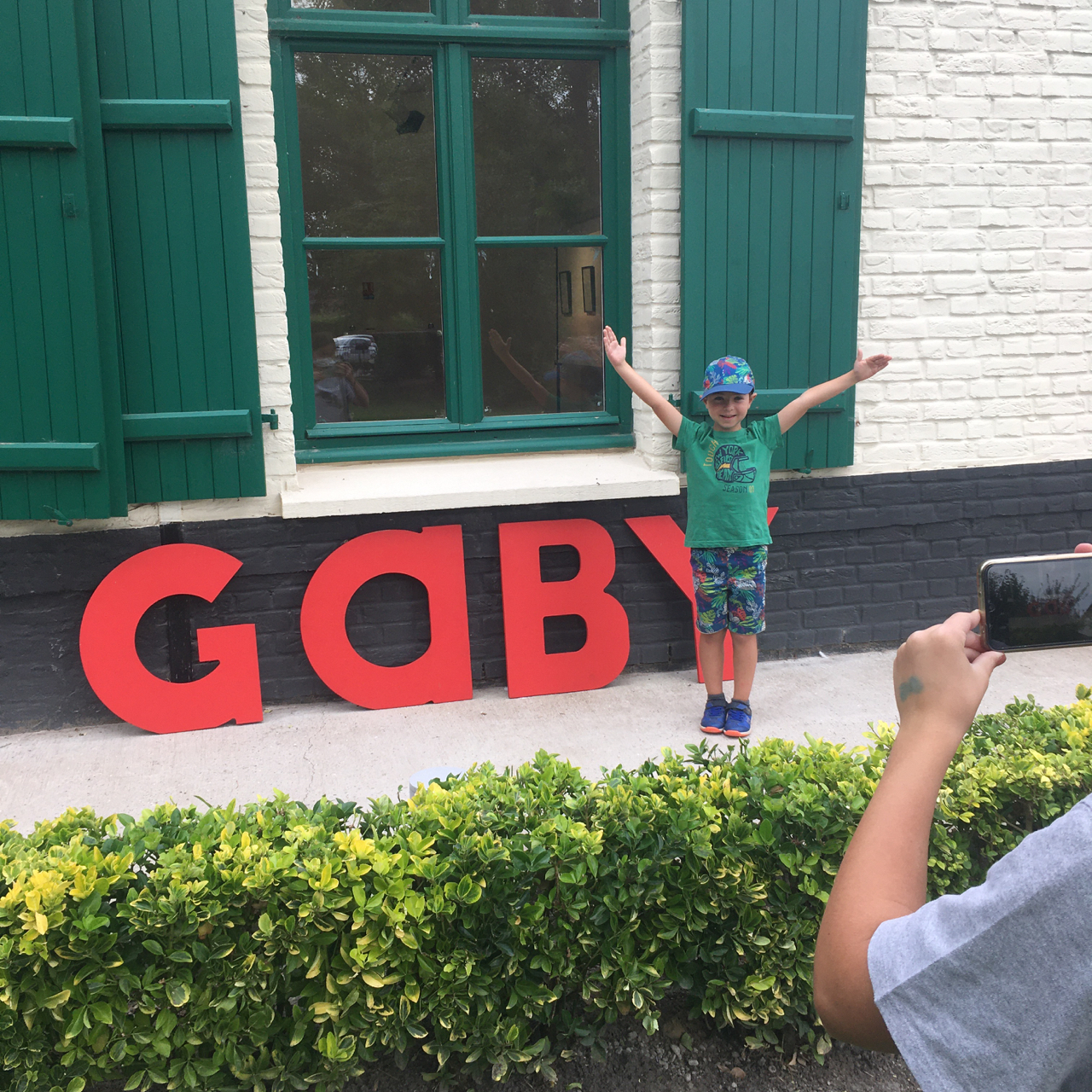
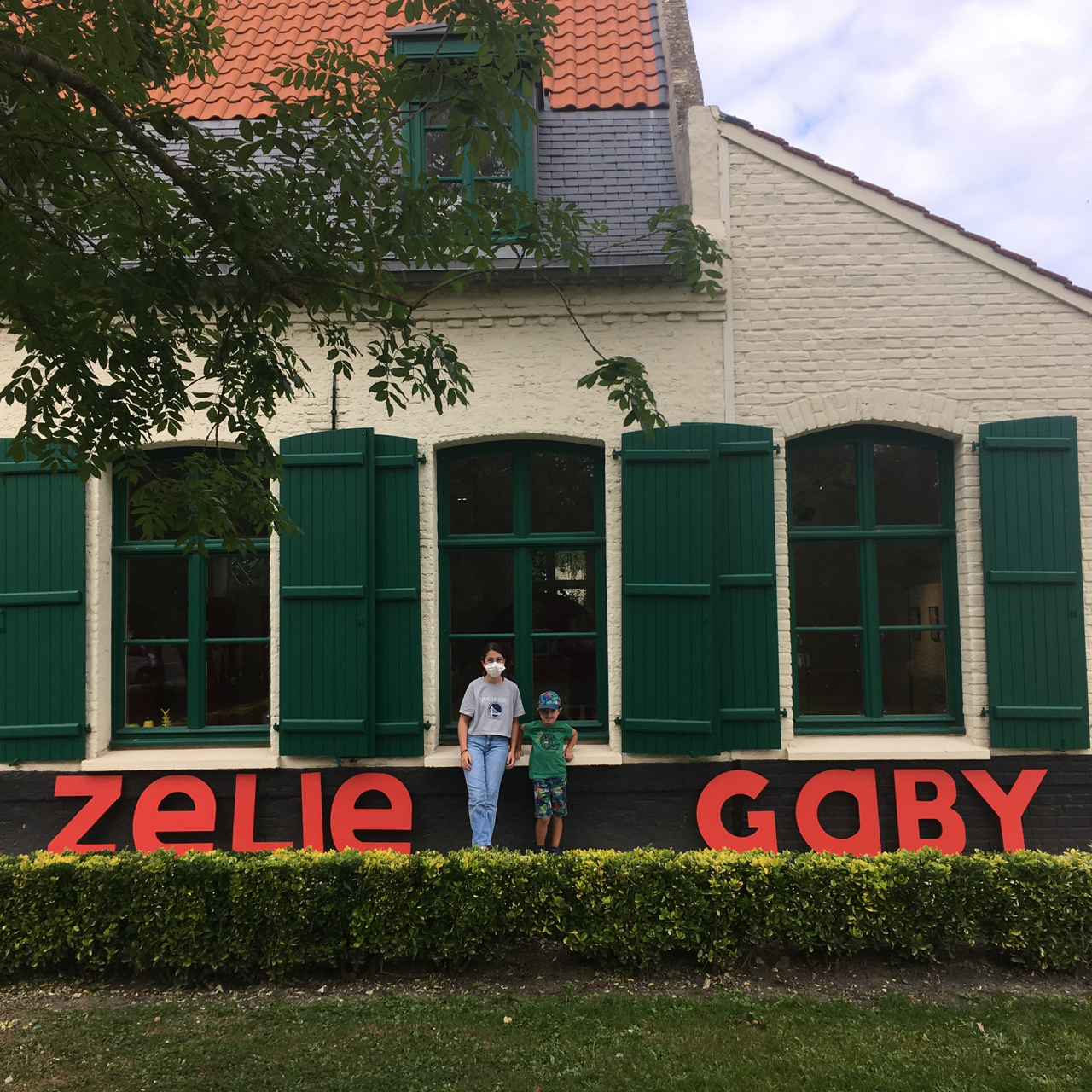
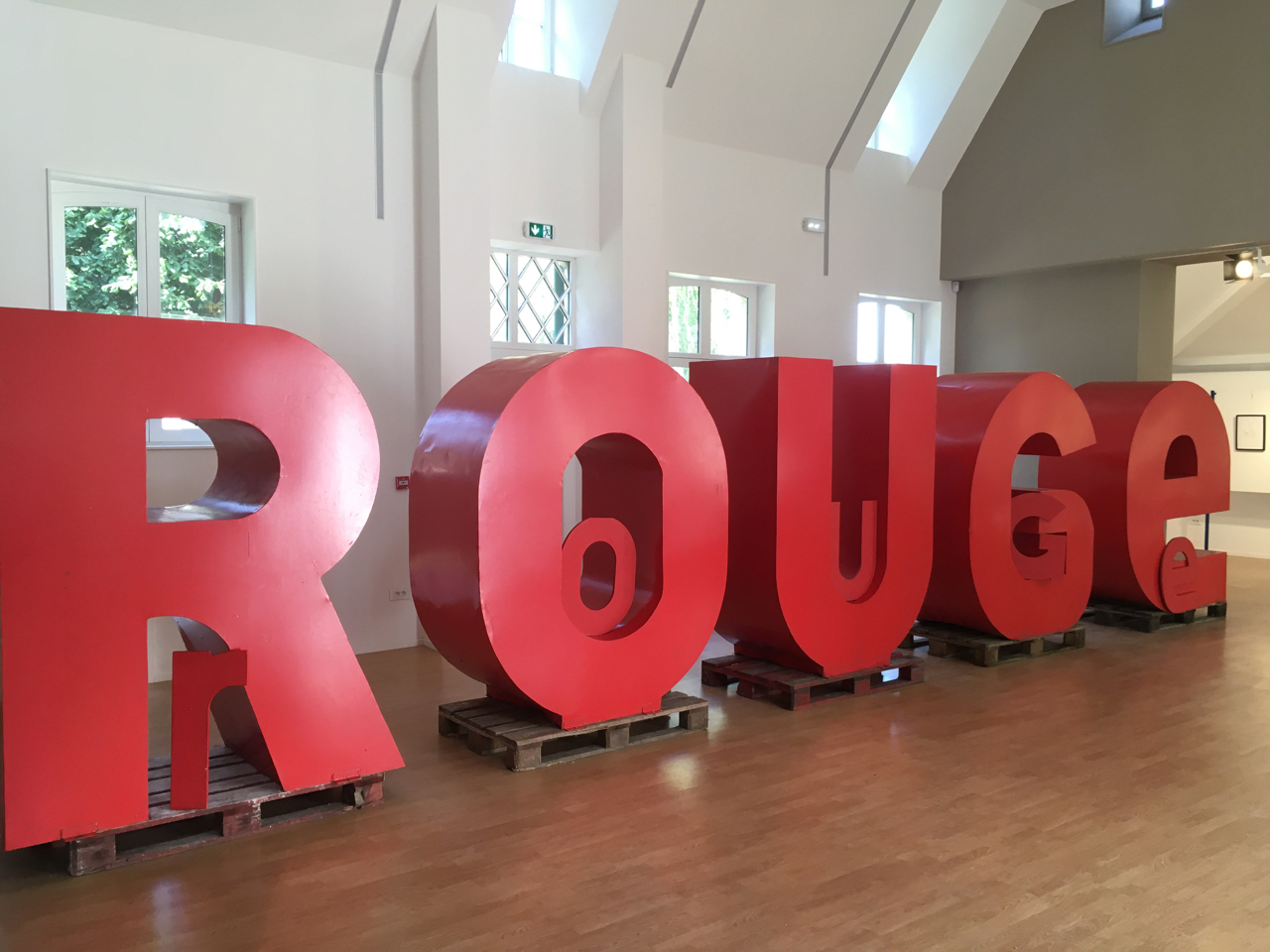
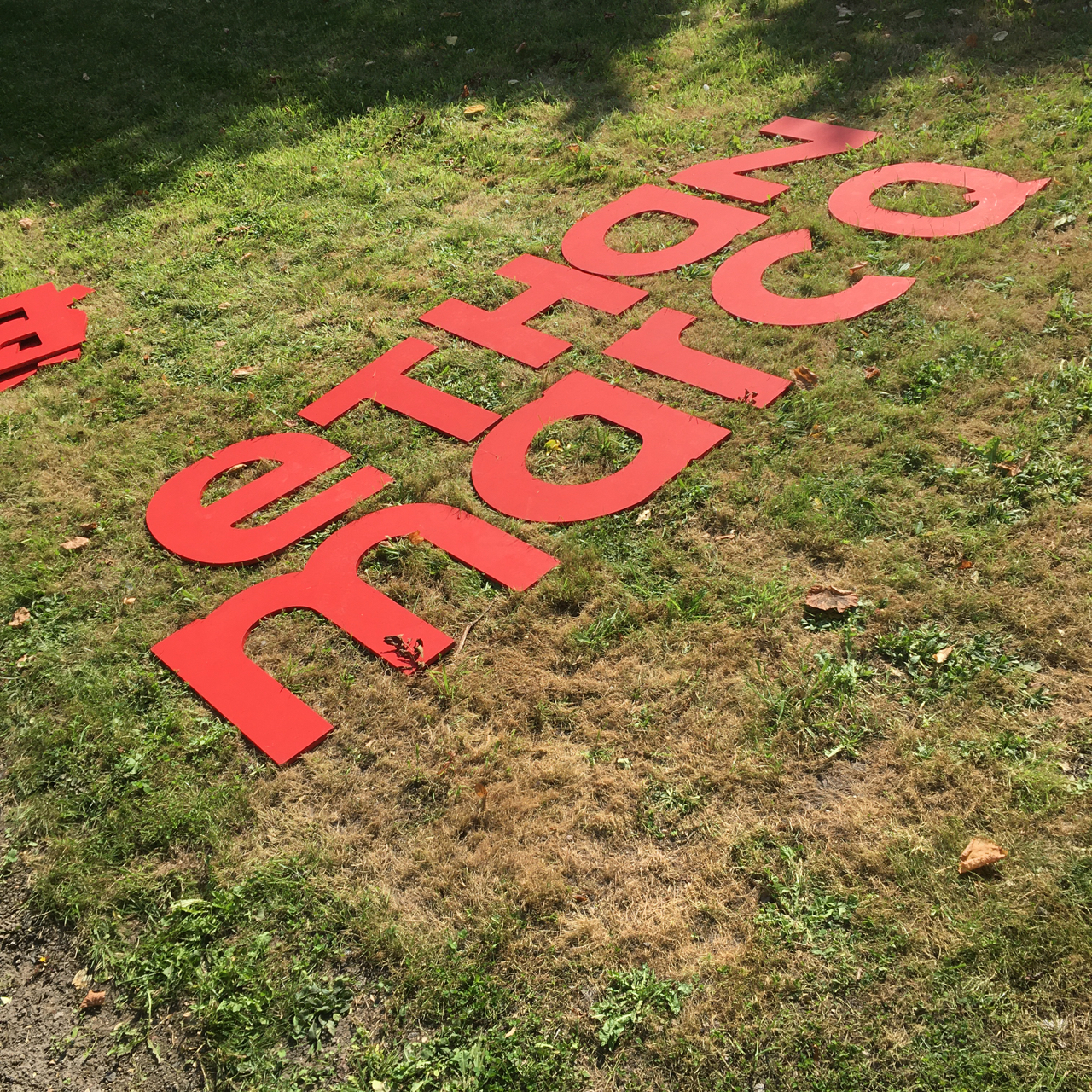
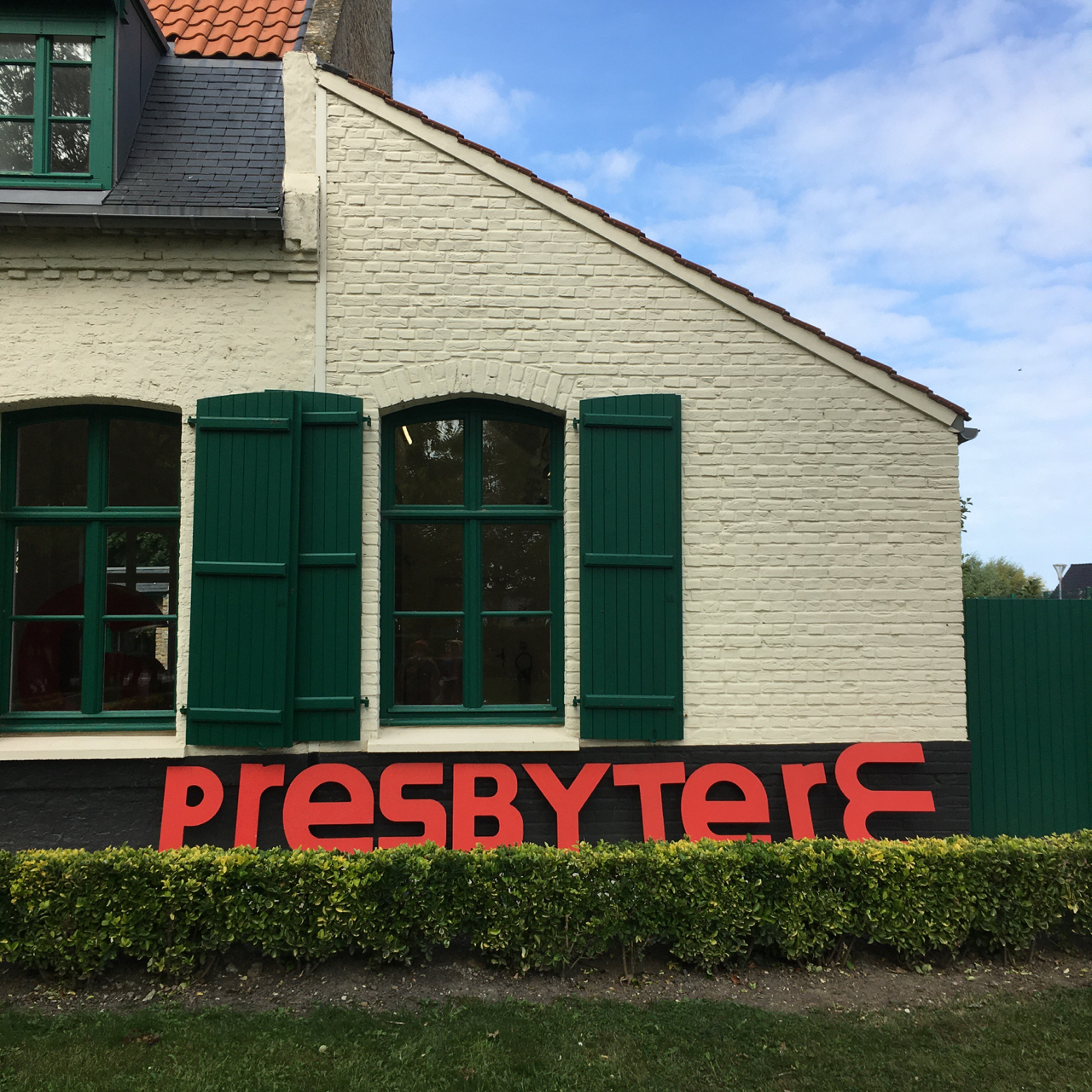
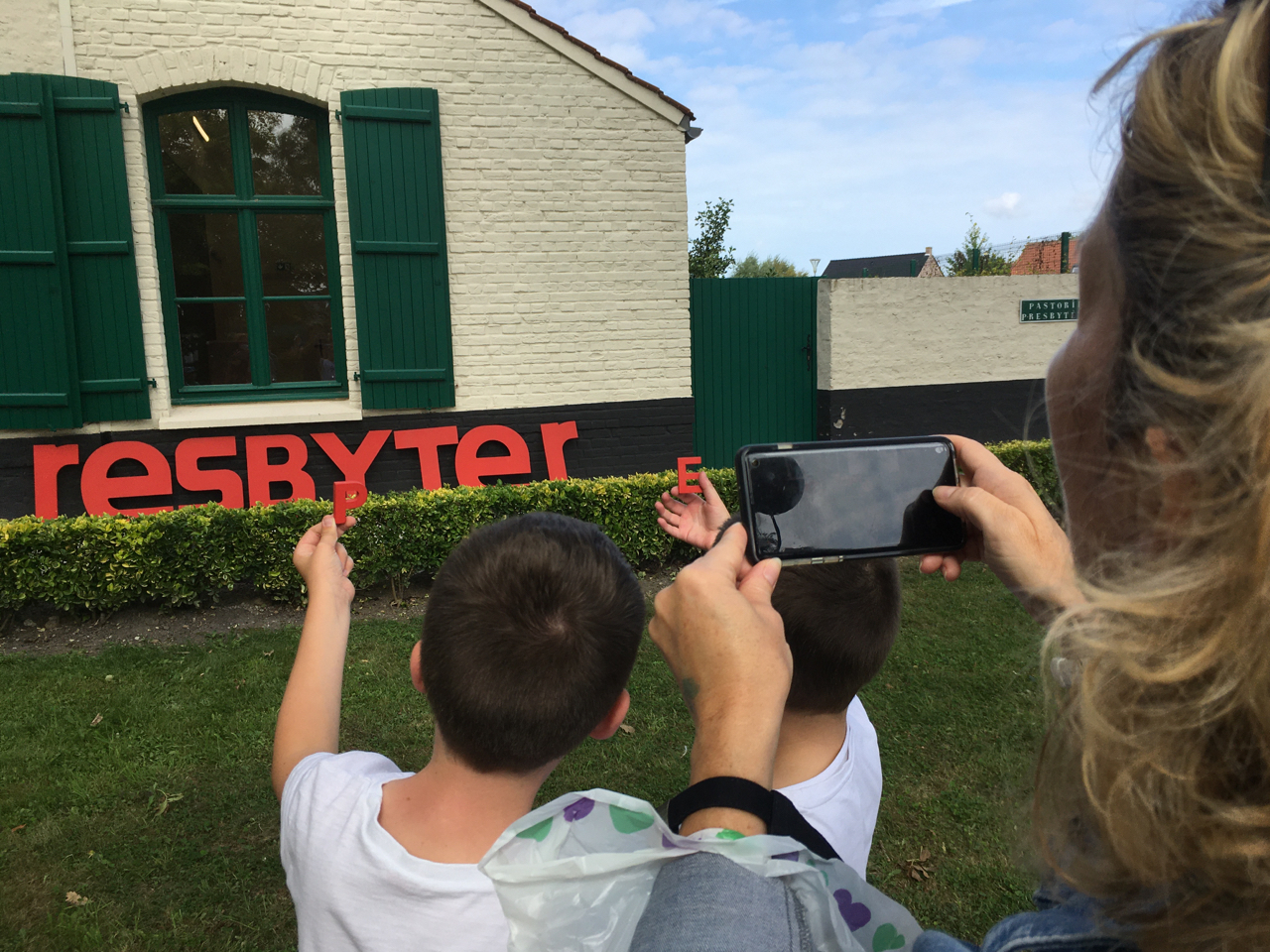
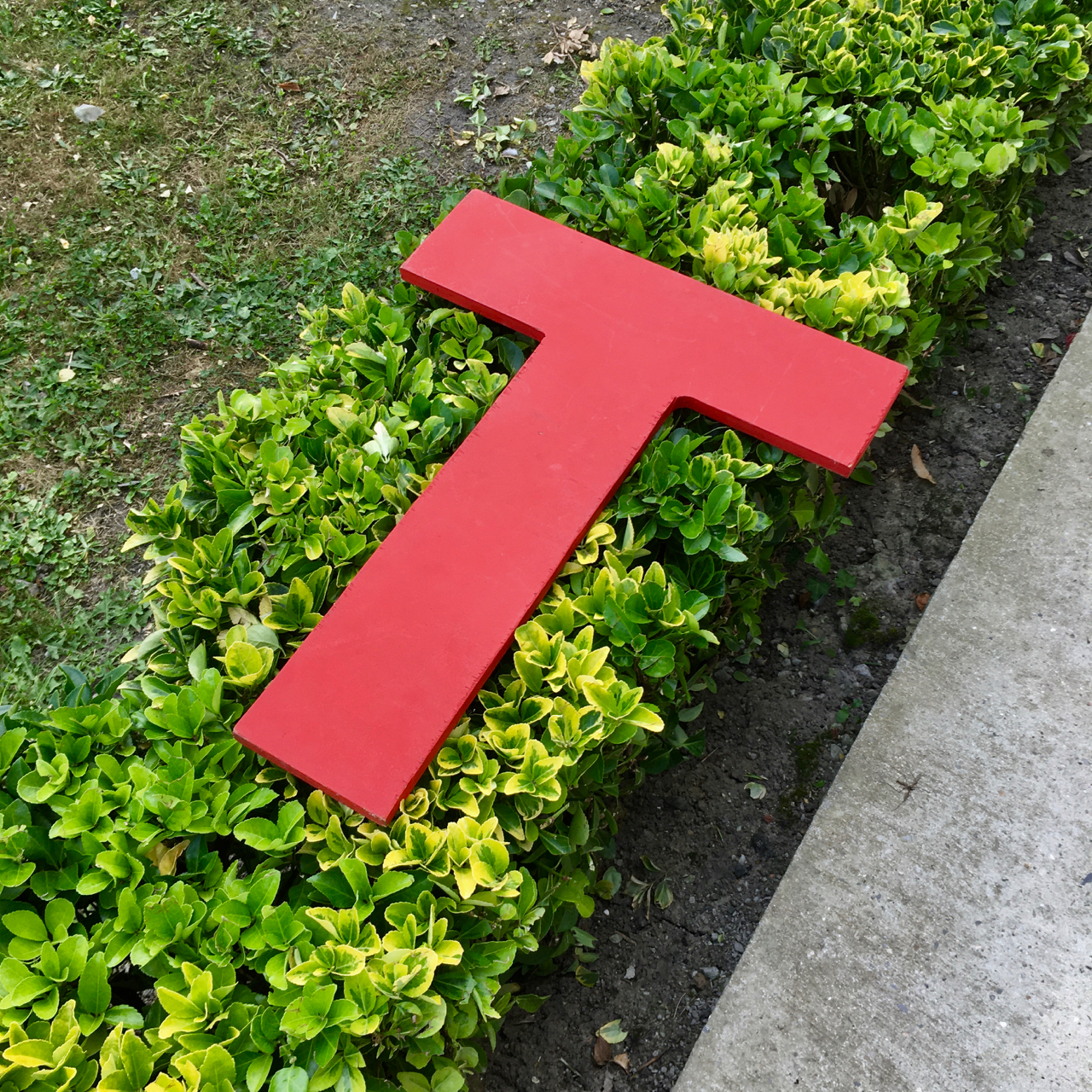
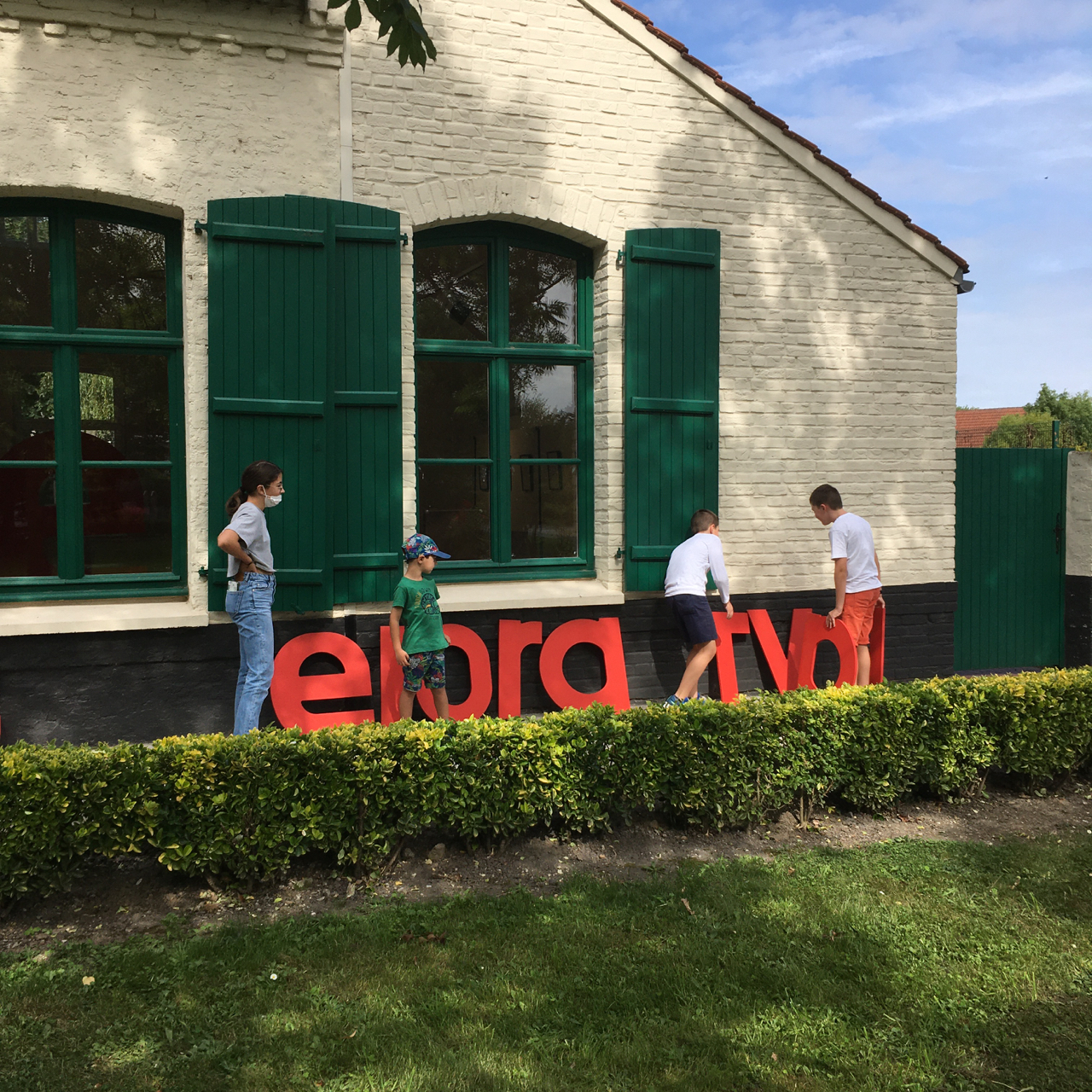
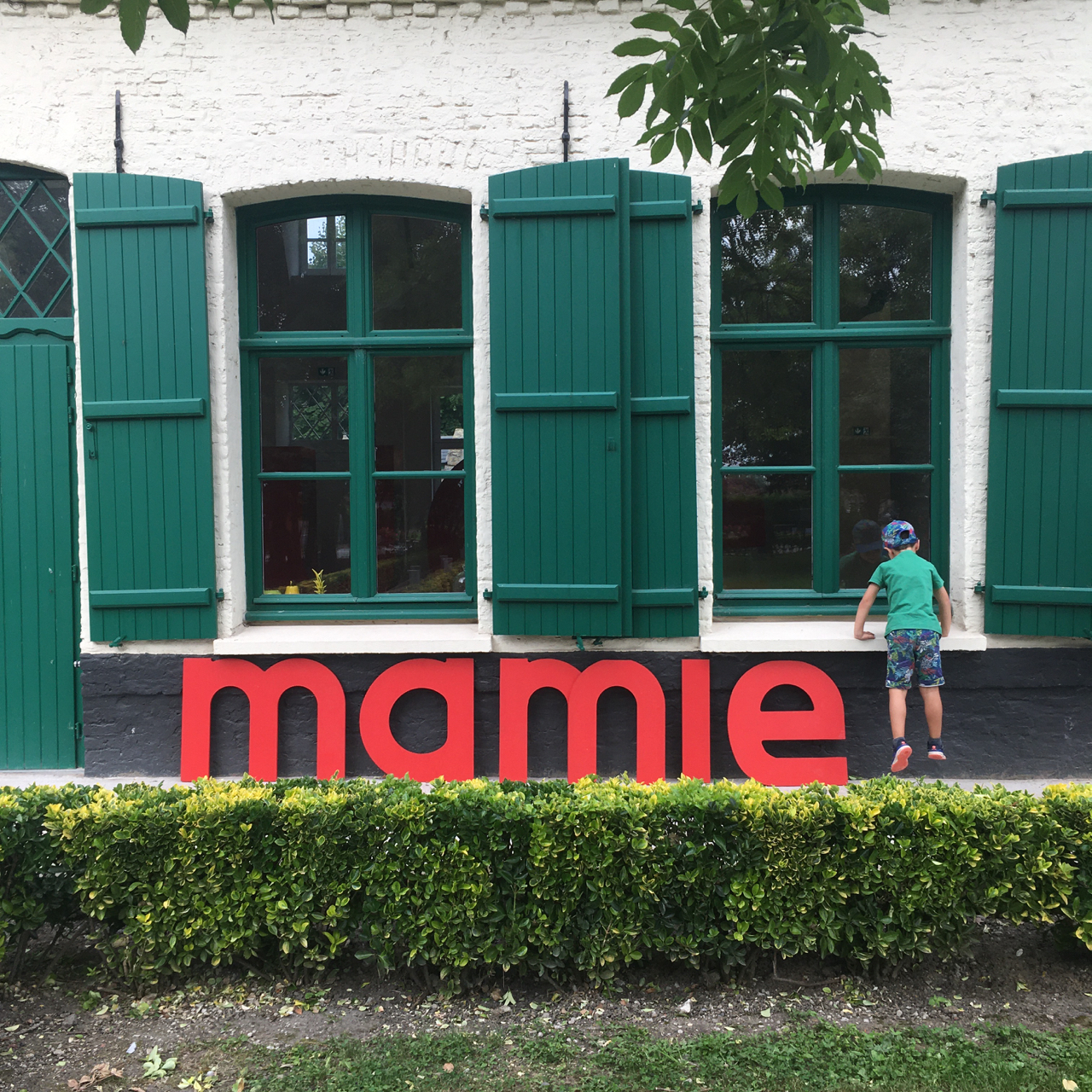
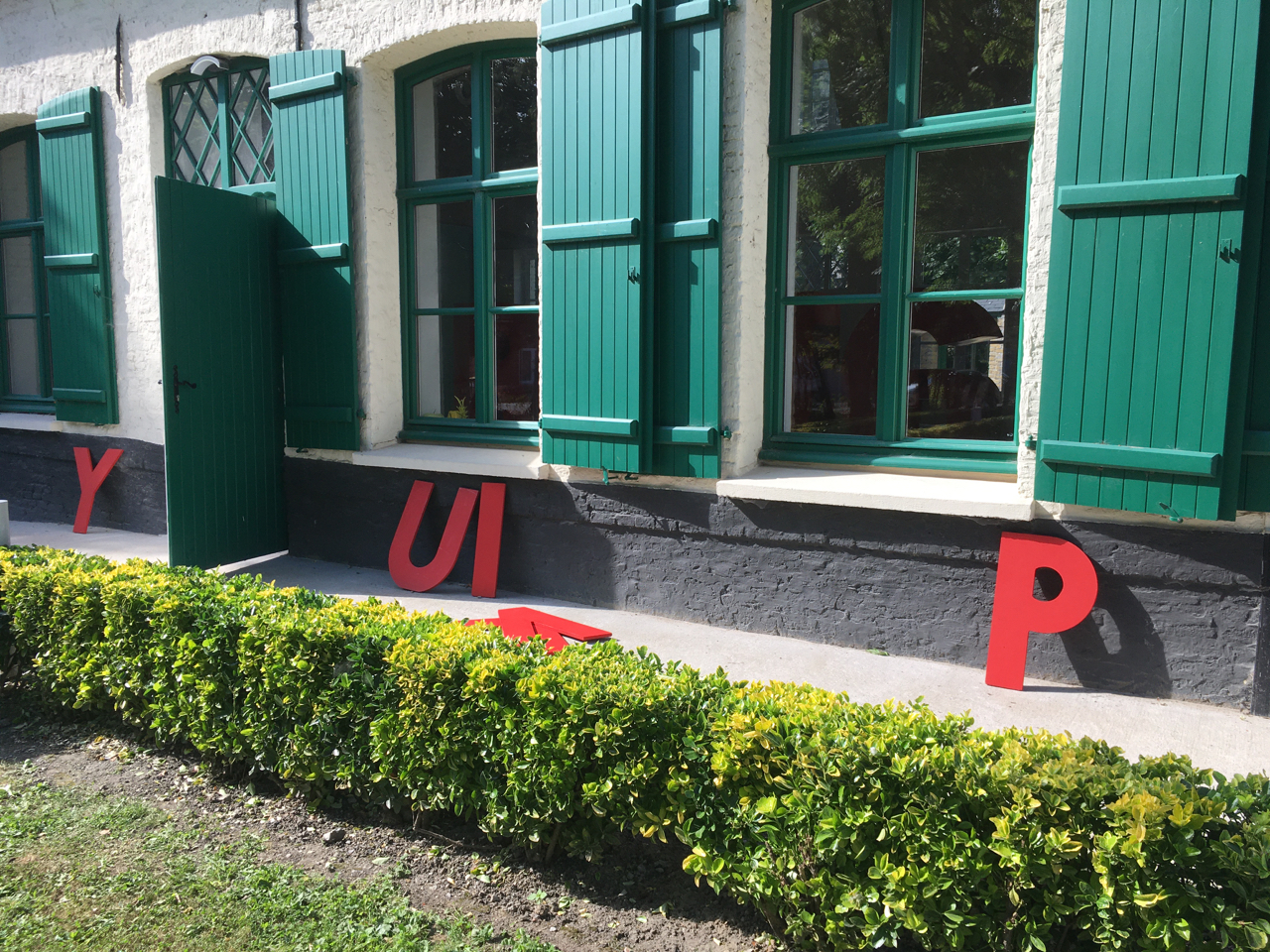
Comme une abstraction
de ce qui se fait.
La boite s’ouvre.
Les lettres rouges sont étalées, paon d’or, roue écarlate.
Et sa boite.
Offrir à tous la possibilité de s’emparer du dispositif : principe même de tout atelier.
Là, au Presbytère de Brouckerque, ce qui passa durant toute la journée est ici, en partie, consigné, en quelques images.
Jeux, de lettres, de mots, de photos prises, très souvent les prénoms, venant comme rejouer les grandes questions liées, de l’identité et du langage.
Que suis-je? Suis-je ce nom, prénom? Me dit-il?
N’est-il pas mon terrain d’ancrage, identitaire, dans le lent gage?
« Qu’y a-t-il dans un nom? La rose ne sentirait-elle pas aussi bon sous un autre nom? »
Roméo et Juliette, William Shakespeare.
Après les prénoms, presque toujours propres, ( Mon prénom est-il un selfie? ), très rares sont ceux qui écrivent les noms de famille, posant les liens qui nous tissent plus amples que soi: ce jour-là, un dimanche, on pensa à une grand-mère: un petit coucou fut fait: « mamie », écrit en rouge, sur le mur du presbytère. Envoyé. Photo.
Et hop, via Families. Partagé.
Arrivé dans le salon de la grand-mère.
Ce jour-là, Ethan Marcq ( je lui donnerai 13 ans? ) signe une oeuvre intéressante, il bricole solo avec les lettres et dans mon dos crée, spontanément, ce « ROUGE/ROUGE » qui me plait bien. J’ai déjà mon ROUGE en rouge, et il en remet une jolie couche! Les petites lettres redisant les grandes redisant la couleur!
J’adore ce genre de tautologie, qui n’en est jamais vraiment une, ni une redite pure, comme ce PRESBYTERE, bricolant les grandes et les petites, jouant avec les règles de perspective photographique pour obtenir une image, un mot, on ne sait plus trop, écrit avec des lettres de même taille. À l’oeil.
Ce « presbytère » en rouge, comme rejouant le panneau sur la droite, en français/flamand. Nommant le lieu qui – je représente ce que je détruis – n’en est plus un. Juste les murs.
Et plein d’histoires hantant le lieu. Liens.
En parlant de liens, dans le fond de la boite, un papier. Un souvenir, la boite laissée après le confinement dans une école de la métropole pour une classe de grande section. Et un petit mot, mode opératoire et direction des opérations par Iris.
D’autres enfants décident de faire la publicité d’une marque de bijou, de leur mère. Les lettres rouges retrouvent leur fonction communicantes premières. C’est de là que vient mon projet. Les enseignes commerciales.
À détourner, pour passer du commerce à la poésie de l’écrit dans l’espace public.
Moi j’ai trouvé un joli « f » au sol, en branche moussue. Il se perd dans la boite des petites lettres, avant de faire, quelques jours plus tard, une réapparition impromptue dans les ateliers scolaires.
Ce « f » m’en rappelle un autre, accroché au mur de mon atelier, qui continue de m’interroger.
Questions persistant, sans trop de réponses précises. Seuil. Il ne m’en faut pas beaucoup, avec certains objets, pour remonter des courants, comme ici, la question qui trotte devant ce « f » : est-ce là l’irruption, au sein d’une nature naturée, d’une nature naturante ?
Le grand mystère de la branche en « f ».
Bref…